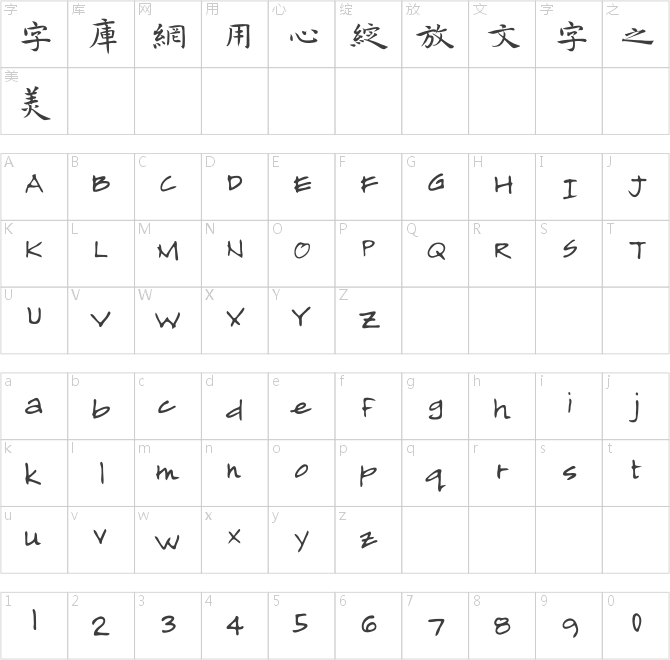
字体名称: 五台楷书
五台楷书
五台楷书介绍
五台楷书,由“生活禅”先行者本觉上人在五台山修持时主导设计、制作的一套楷书字体。集体成库,发行流通,惠施大众,同品禅韵。   五台楷书,溯源于禅心,师法于禅门机锋古趣,含八大山人之潇洒自在;俱弘一法师之圆融洁净。显修证者抵心源之寂寂,涌自性之妙趣!以禅入墨,似本觉朗照之孤明无际;以墨写心,如流芳大千之妙用恒沙!五台楷书,细细品之,似文殊持慧剑斩绝翳秽,如观音洒甘露普施清凉,涤人心肺,滤人思绪。